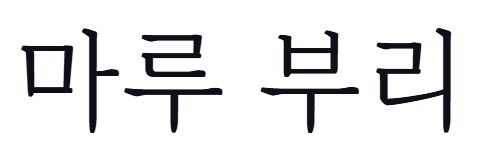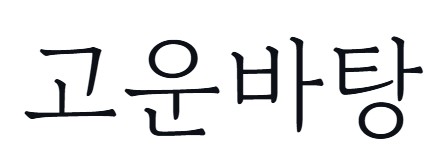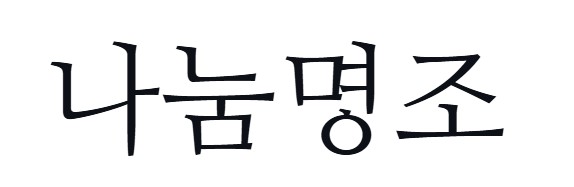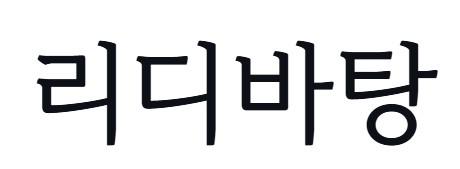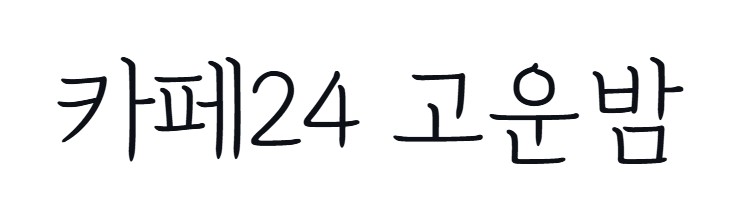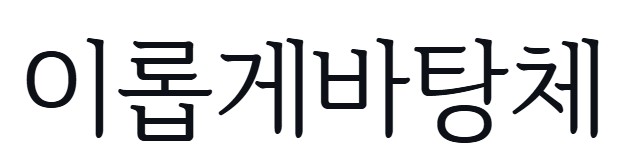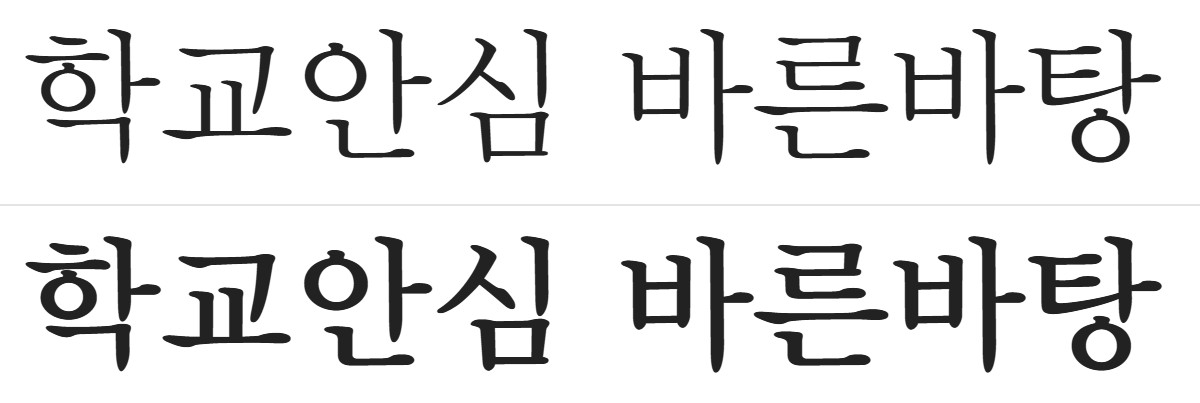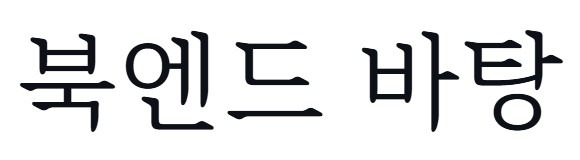
가독성이 뛰어나고 고전미가 느껴지는 명조체는 인쇄물이나 긴 글을 읽기 좋은 서체로 널리 사용됩니다. 오늘은 본문용으로 활용하기 좋은 무료 명조체 10종을 소개합니다. 웹 문서, 책자, 보고서, 뉴스레터 등에 잘 어울리는 서체들을 선정했어요.
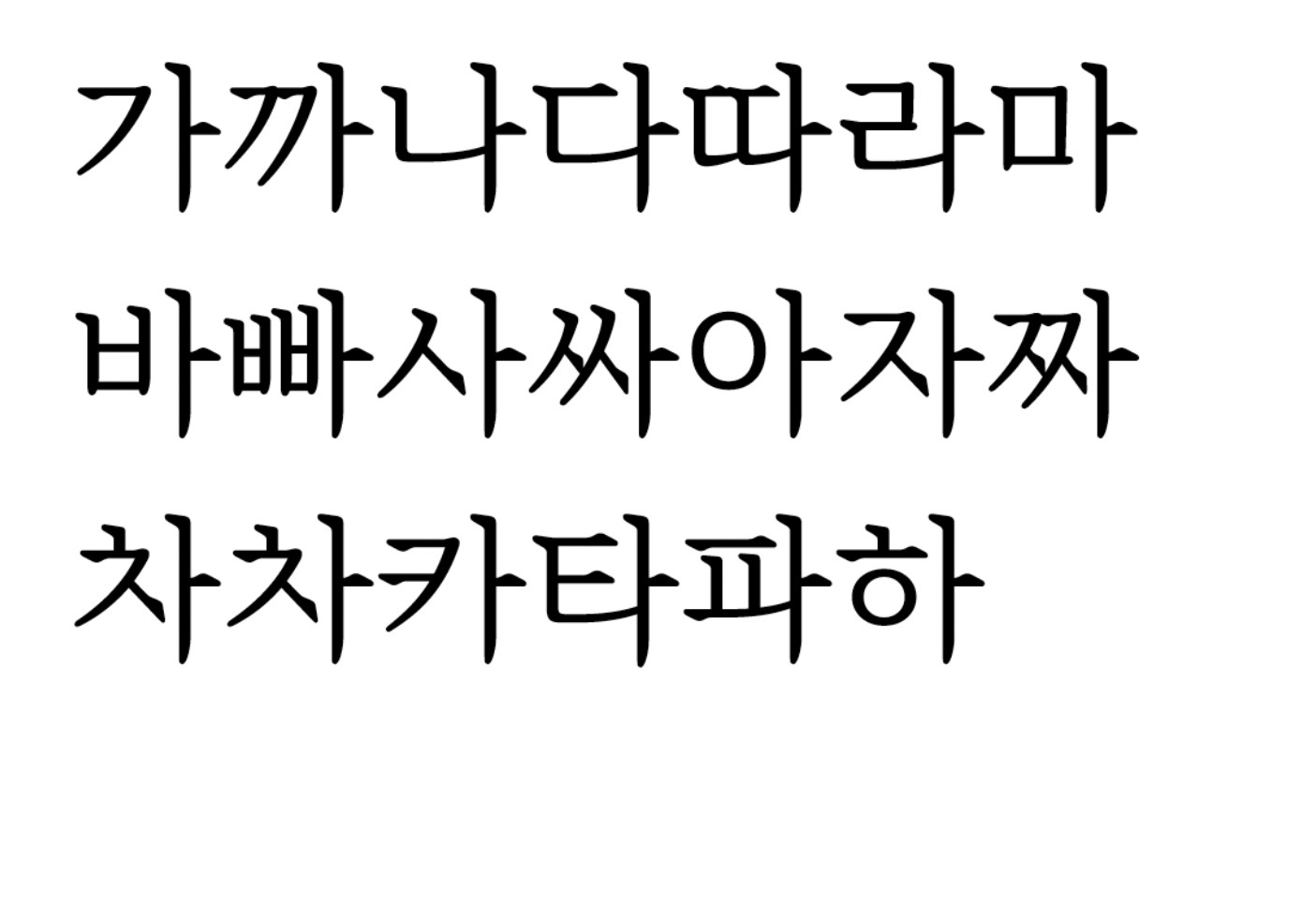
5. 본명조 (Noto Serif KR)
설명: 구글과 어도비가 공동 개발한 범용 명조체
형태: 정통 명조 기반, 다양한 디바이스에서 깔끔하게 보임
굵기 종류: 8단계
용도: 웹 문서, 모바일 콘텐츠, 멀티 플랫폼 문서
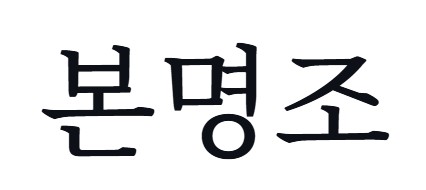
6. 카페24 고운밤
설명: 고운 곡선과 잔잔한 분위기가 특징인 감성 명조체
형태: 부드럽고 둥근 획, 감성적 느낌 강조
굵기 종류: 1단계
용도: 수필, 감성 블로그, 편지 콘텐츠
9. 북엔드 바탕
설명: 전통 명조 기반에 현대적 디테일을 더한 본문 서체
형태: 단단하고 안정적인 자소 구성
굵기 종류: 2단계
용도: 출판용 본문, 리뷰 콘텐츠
10. 학교안심 산뜻바탕
설명: 학교안심 시리즈 중 명조 스타일의 부드러운 서체
형태: 명조 기반에 약간의 감성 터치
굵기 종류: 2단계
용도: 수업자료, 안내문, 동화 본문